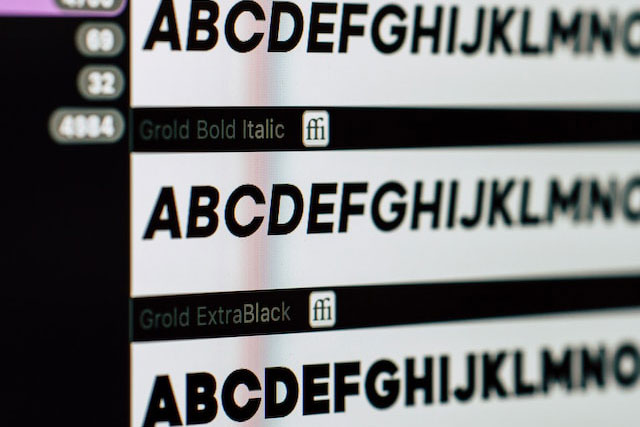
웹 타이포그래피
웹 타이포그래피(Web typography)는 웹사이트 디자인에 사용되는 폰트, 크기, 줄간격, 글자간격 등과 같이 텍스트의 스타일과 레이아웃을 다루는 디자인 영역을 말합니다. 웹 타이포그래피는 웹사이트의 시각적 품질, 사용자의 콘텐츠 이해 및 전반적인 사용자 경험에 중요한 영향을 미칩니다. 콘텐츠의 가독성을 높여 사용자의 읽기 경험을 향상하는데 도움을 주며, 적절하게 구성되고 조화롭게 통합된 웹 타이포그래피는 웹사이트를 더 매력적으로 만듭니다.
웹 타이포그래피는 웹사이트의 시각적 분위기를 형성하는 데 중요합니다. 폰트 스타일과 크기, 색상 선택은 웹사이트의 느낌과 브랜드 아이덴티티를 반영하며, 사용자에게 웹사이트의 성격을 전달할 수 있습니다. 예를 들어, 친근하고 따뜻한 브랜드는 부드러운 폰트와 따뜻한 색상을 사용할 수 있습니다. 웹 타이포그래피를 사용하여 특정 요소를 강조하고 사용자의 시선을 특정 방향으로 유도할 수 있습니다. 제목, 부제, 링크 또는 중요한 내용을 강조하면 사용자가 중요 정보에 주목할 수 있습니다.
웹 타이포그래피 요소
폰트 패밀리는 디자인 요구사항에 따라 텍스트를 스타일링하는 데 사용됩니다. 예를 들어, 본문 텍스트에는 Regular, 제목 텍스트에는 Bold 스타일을 적용할 수 있습니다. 이러한 다양한 스타일 옵션은 웹사이트의 디자인을 풍부하게 만들어 시각적 다양성을 제공하고 사용자에게 중요한 정보를 강조하는 데 도움을 줍니다.
글자 크기는 가독성에 큰 영향을 미칩니다. 가독성은 콘텐츠가 얼마나 쉽게 읽히는지를 나타내는 요소입니다. 적절한 글자 크기는 글과 공간 간의 관계를 보다 명확하게 만듭니다. 이것은 사용자가 글자를 인식하고 단어, 문장, 단락 등의 구조를 이해하는 데 도움을 줍니다. 제목, 본문 텍스트, 부제목 및 주요 내용의 글자 크기를 조절하여 사용자가 편안하게 읽을 수 있도록 해보세요. 본문 글자 크기는 일반적으로 16~18px 정도를 사용합니다.
줄간격과 글자간격을 조절하여 텍스트가 밀집되지 않도록 하고, 한번에 읽는 글자의 양을 조절하세요. 적절한 간격은 텍스트를 눈에 띄게 만듭니다. 글자색과 배경색의 대비를 고려하여 가독성을 높입니다. 텍스트가 배경과 충분히 대비가 있는 색상을 선택하세요.
텍스트 스타일(볼드체, 이탤릭체, 밑줄, 강조, 목록 스타일)을 사용하여 텍스트의 중요성을 강조하고 콘텐츠 구조를 명확하게 만듭니다. 모바일 기기와 데스크톱 화면에서도 가독성을 유지하도록 웹사이트의 타이포그래피를 조절하는 반응형 디자인을 고려하세요. 웹 타이포그래피는 웹사이트의 외관과 사용자 경험에 큰 영향을 미치며, 콘텐츠를 눈에 띄고 읽기 쉽게 만드는데 중요합니다.
웹 폰트 사용 시 체크사항
웹 폰트는 웹에서 사용하기 위해 만들어진 폰트로, 웹사이트에서 특정 글꼴을 화면에 표시할 수 있게 해줍니다. 웹폰트 서비스 또는 폰트 파일을 통해 웹사이트에 적용할 수 있습니다. 웹폰트 파일을 사용할 때 고려해야 할 몇 가지 중요한 점이 있습니다.
1. 브라우저 호환성: 웹폰트를 선택할 때, 대부분의 주요 웹 브라우저에서 지원하는 형식인 WOFF(웹 오픈 폰트 포맷)나 WOFF2를 사용하는 것이 좋습니다. 이를 통해 브라우저 호환성을 확보할 수 있습니다.
2. 웹폰트의 크기: 웹폰트 파일은 다운로드 시간을 늘릴 수 있으므로 파일 크기를 최소화하는 것이 중요합니다. 압축된 웹폰트 파일을 사용하거나 서비스 제공업체가 제공하는 최적화된 웹폰트를 선택하실 수 있습니다.
4. 성능 최적화: 웹폰트를 불러오는 동안 페이지의 렌더링이 느려지는 것을 방지하기 위해 웹폰트를 비동기로 로드하거나, FOIT(Flash of Invisible Text)과 FOUT(Flash of Unstyled Text)를 최소화하는 방법을 고려해야 합니다.
5. 폰트 스타일 및 크기: 웹사이트의 디자인과 일치하도록 웹폰트의 스타일과 크기를 조절해야 합니다. 반드시 가독성을 유지하면서 사용자 경험을 향상시켜야 합니다.
6. 대체 폰트 설정: 선택한 웹폰트가 사용자의 브라우저에서 로드되지 않을 경우를 대비해 대체 폰트 설정을 고려해야 합니다. 웹폰트 뒤에 일반적인 웹 안전 폰트를 제공하는 것이 좋습니다.
7. 테스트와 디버깅: 웹폰트를 사용하기 전에 여러 브라우저와 디바이스에서 테스트하고, 다양한 상황에서 폰트가 올바르게 표시되는지 확인해야 합니다.
8. CDN 사용: 웹폰트를 빠르게 로드하려면 CDN(Content Delivery Network)을 사용하는 것이 좋습니다. CDN은 폰트 파일을 사용자에게 빠르게 전달하는 데 도움을 줍니다.